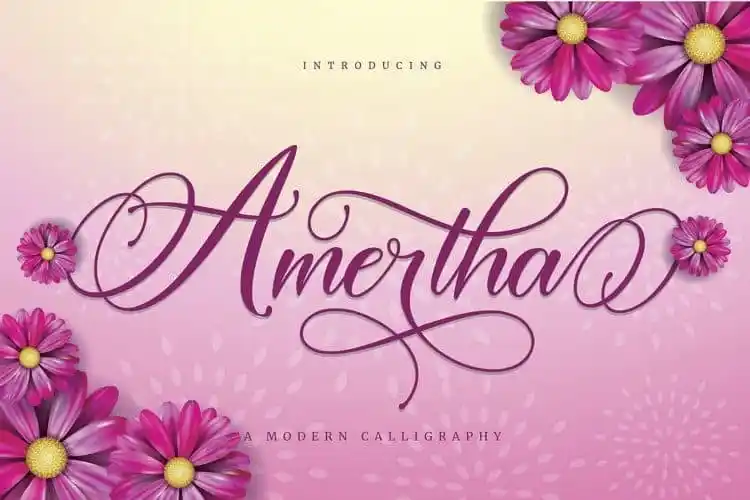
Amertha Calligraphy Font – Download Grátis
Introduzimos uma nova fonte de escrita amertah calligraphy que traz sempre a sensação de beleza, delicadeza, elegância e estética em cada traço. Esta fonte moderna de escrita é perfeita para elevarem qualquer ideia de arte à sua máxima expressão. O destaque para esta fonte está no seu conjunto de swash que vem incluído, permitindo-lhe adicionar detalhes decorativos sem precisar de muito esforço. Além disso, a característica PUA encoded permite-lhe facilmente acessar todos os caracteres mágicos e swashes da sua seleção. Com esta fonte de escrita amertah calligraphy na sua arsenal de ferramentas criativas, você não terá mais o que fazer para dar um toque elegante a qualquer projeto. Sem dúvida é uma excelente escolha para quem busca uma fonte moderna e sofisticada.